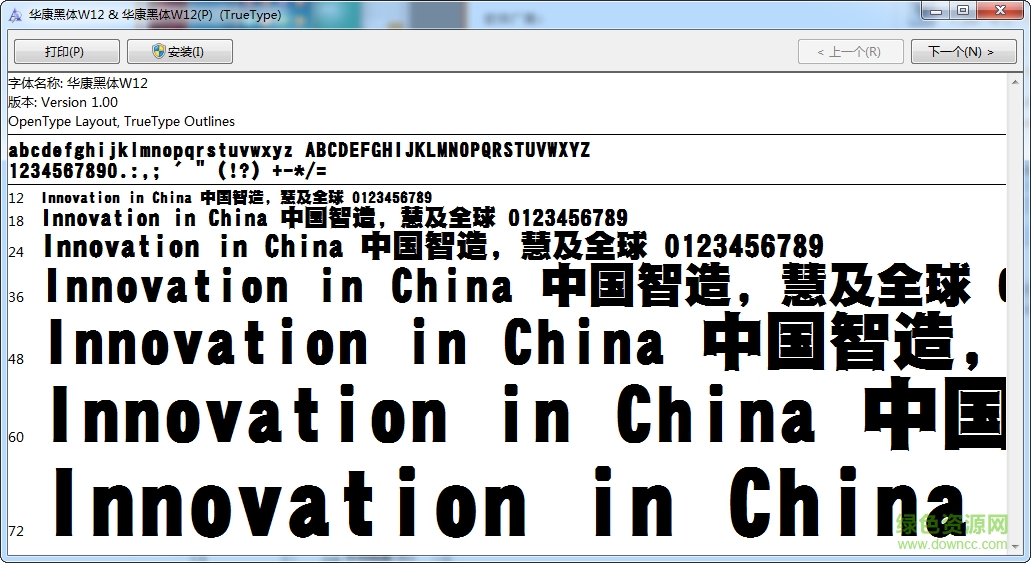
dfpheiw12 regular字體是華康黑體系列中最粗的一款,w5、w9、w3、w7等相關(guān)華康字體綠色資源網(wǎng)均提供了下載包,不論是做PPT、PS圖案還是海報設(shè)計都用得上!
清末萌芽57年簡化字體后定形。筆劃橫平豎直,粗細(xì)一致,筆劃較粗,方頭方尾形成方黑一體而得名,又稱方體。特點(diǎn):由宋體結(jié)構(gòu),筆劃單純,相互大方,醒目粗壯。
華康黑體保留了傳統(tǒng)黑體之設(shè)計形象,起筆處有著近似明體的外形與風(fēng)格,與現(xiàn)代黑體的簡率略有不同。此系列具備明快感,骨格外馳內(nèi)張,又增添了些許古刻版之風(fēng)。搭配華康黑體同系列產(chǎn)品,以不同粗細(xì)呈現(xiàn)內(nèi)文、標(biāo)題字相當(dāng)?shù)靡诉m中。特別適用于一般文書、辦公文件、報表或雜志內(nèi)文字。